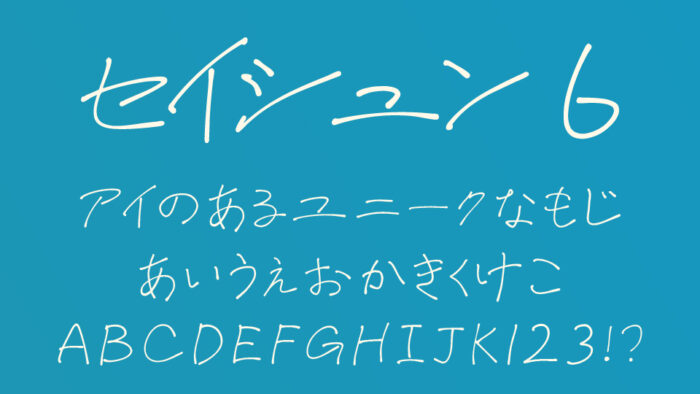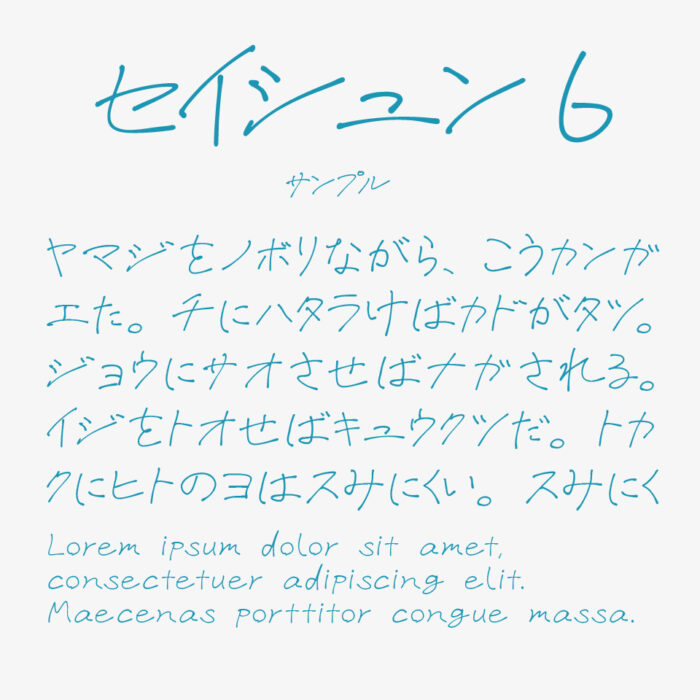
青春6フォント
青春6フォントフォントは、軽やかでまっすぐな筆跡が特徴の、青春らしさがにじむ手書きフォントです。
ボールペンで書かれているような細さやインクの滲みが再現されており、線のかすれや少し跳ねるような動きが、勢いと前向きな気持ちが感じられる絶妙なバランスが、学生時代のノートや手紙の文字を彷彿させてる青春感のある手書き文字です。
現バージョンは漢字の文字収録はありませんが、今後追加されていく予定とのことです。
収録文字は、ひらがな・カタカナ・アルファベット・数字・記号が収録されています。